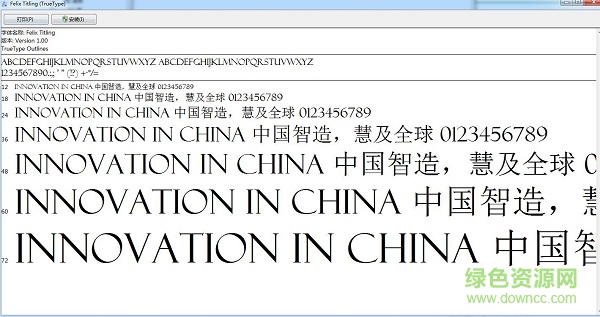
felixtitlingmt.ttf字體
felix titling和felix titling mt兩款字體是綠色資源網(wǎng)為大家整理的小眾英文字體打包合集,該字體采用極細(xì)襯線設(shè)計(jì),有一種高冷的氣質(zhì),適合用在時(shí)尚雜志領(lǐng)域,有需要者歡迎免費(fèi)下載!